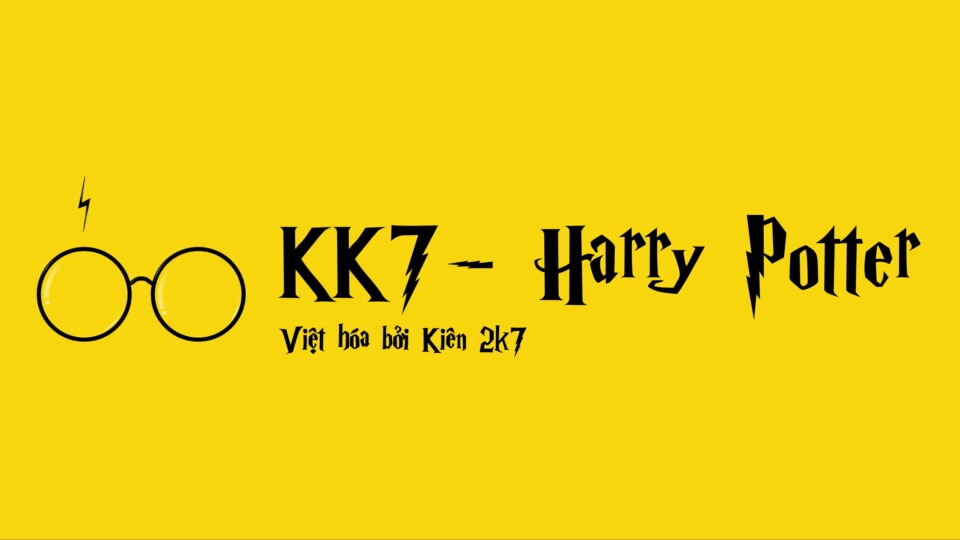
Font Việt Hóa KK7-Harry Potter
Giới thiệu về bộ Font Việt Hóa KK7-Harry Potter
Chào mừng các bạn đến với thế giới phù thủy kỳ bí thông qua bộ Font Việt Hóa KK7-Harry Potter cực kỳ ấn tượng. Đây là phiên bản phông chữ được lấy cảm hứng trực tiếp từ tiêu đề của loạt phim và truyện đình đám Harry Potter, giúp người dùng tái hiện lại không gian ma thuật đặc trưng. Điểm đặc biệt của bản Font Miễn Phí này chính là sự tỉ mỉ trong việc thiết kế các ký tự mang đường nét sắc sảo, uốn lượn như những tia chớp và nét bút lông cổ điển. Việc cài đặt bộ chữ này sẽ giúp các dự án sáng tạo của bạn trở nên sống động và đậm chất điện ảnh hơn bao giờ hết.
Ưu điểm của phông chữ ma thuật
Bộ Font Việt Hóa KK7-Harry Potter đã được tối ưu hóa hoàn toàn để hỗ trợ gõ tiếng Việt có dấu mà không bị lỗi hiển thị. Điều này cực kỳ quan trọng đối với các bạn học sinh và giáo viên khi muốn thiết kế slide bài giảng, làm báo tường hoặc trang trí thiệp mời cho các sự kiện của trường lớp. Với định dạng linh hoạt, bạn có thể dễ dàng sử dụng phông chữ này trên nhiều phần mềm khác nhau như Microsoft Word, PowerPoint hay Adobe Photoshop. Mỗi ký tự đều giữ được cái “hồn” của tác phẩm gốc, mang lại cảm giác hoài cổ nhưng cũng đầy sức mạnh sáng tạo.
Cách sử dụng và ứng dụng thực tế
Để tận dụng tối đa vẻ đẹp của Font Việt Hóa KK7-Harry Potter, bạn nên sử dụng cho các tiêu đề lớn hoặc các cụm từ nhấn mạnh. Do đặc thù đường nét cách điệu cao, phông chữ này tỏa sáng nhất khi làm nổi bật tên chủ đề hoặc tiêu đề chương sách. Kết luận lại, đây là công cụ không thể thiếu cho những ai yêu thích phong cách kỳ ảo. Hãy nhanh tay tải về Font Miễn Phí, Font Việt Hóa, Font Việt Hóa KK7-Harry Potter để bắt đầu hành trình sáng tạo phép thuật ngay hôm nay.